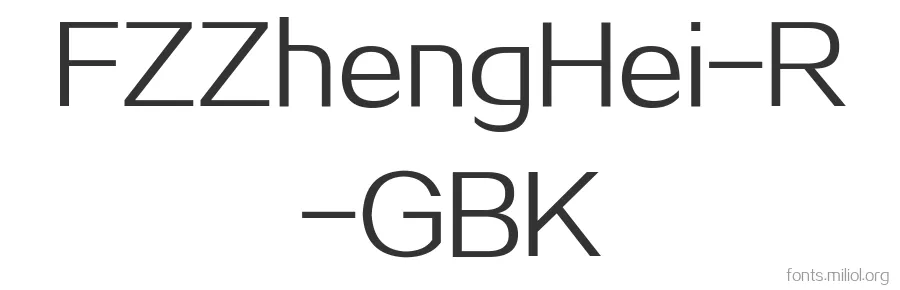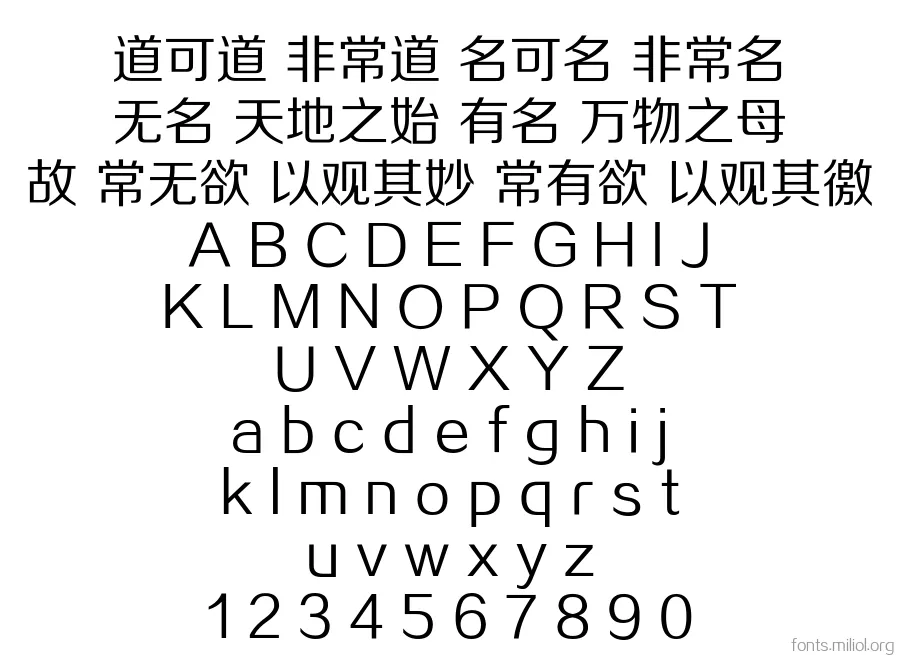
FZZhengHei-R-GBK(方正正黑)字体下载
**FZZhengHei-R-GBK(方正正黑)字体简介**
FZZhengHei-R-GBK是方正字库推出的一款现代黑体字体,以其简洁、规整的笔画和良好的可读性受到广泛欢迎。该字体采用GBK编码标准,支持中、英、日、韩等多国字符,适用于印刷、广告、网页设计等多种场景。
方正正黑的字形设计平衡了传统黑体的稳重与现代设计的灵动感,横平竖直的笔画中融入细微的弧度变化,使整体视觉效果既严谨又不失柔和。其字重适中,标题与正文皆适用,尤其在屏幕显示时能有效降低视觉疲劳。
总之,方正正黑以其通用性和实用性,成为中文设计领域的经典选择之一。